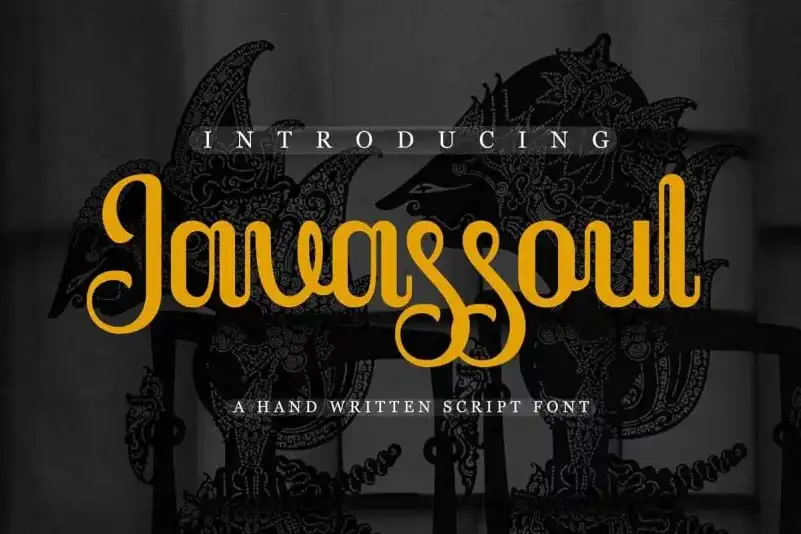
Javassoul Script Font – Download Grátis
Javassoul Script Font é uma fonte divertida e única que traz a essência das receitas criativas para seu projeto de design. Com um toque ligeiramente engraçado, essa fonte parece ser perfeita para o universo da criação e do crafting. Seja para criar marcas com texturas interessantes ou para decorar postais e camisetas, Javassoul Script é um excelente recurso para qualquer tipo de design. Suas letras vibrantes e quirkily são ideais tanto para criações de marca quanto para trabalhos de texto e editoriais. Além disso, essa fonte versátil é ideal tanto para produtos comerciais como para designs digitais. Javassoul Script é uma escolha sólida e divertida que certamente irá enriquecer qualquer projeto de design, especialmente para amantes da criação artesanal.